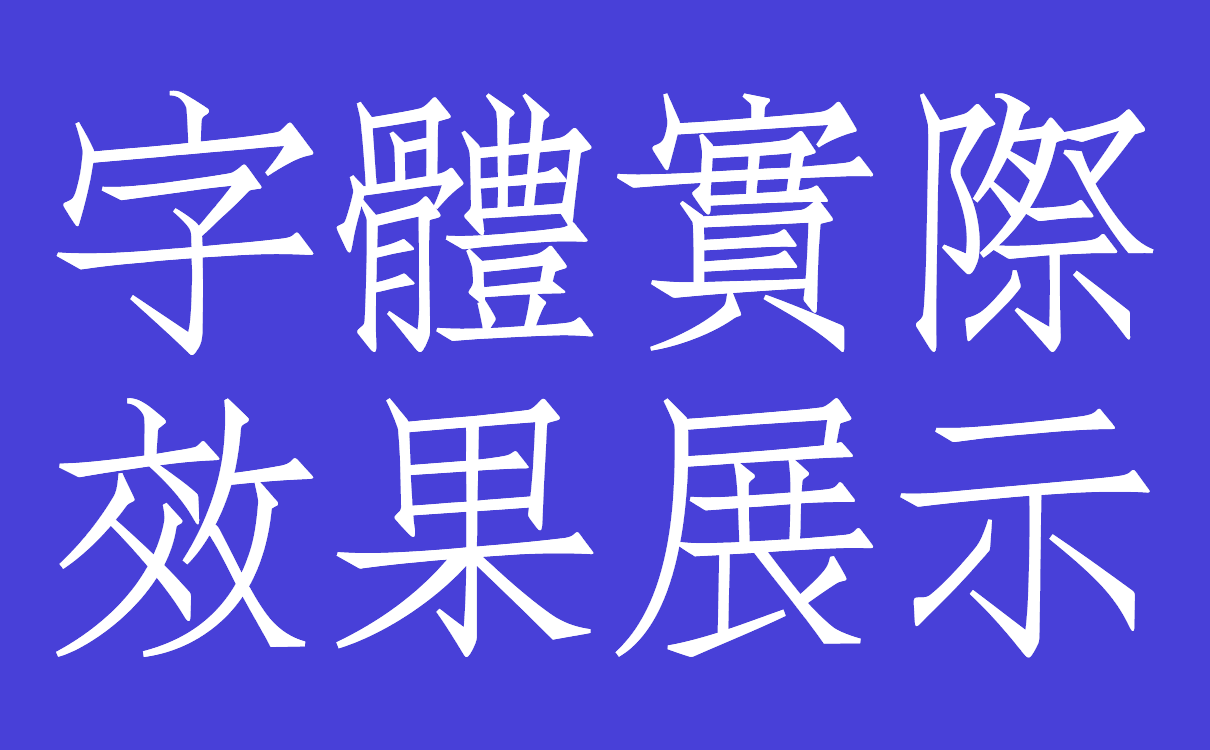
文悦民国仿宋
「文悦民国仿宋」复刻自求古斋摹宋四号方体。摹宋是民国时期除聚珍仿宋外的另一套著名仿宋铅字,它们有着不一样的个性。
本字体基本按原样进行制作,对于原字体中存在的部分文字造型不够整齐、统一的问题,我们并没有过多去纠正,而是作为一种特征,把这份不规整感继承了下来。所以,或许这并不是一款成熟、实用的字体,却是一个不那么严肃的、富有趣味的字体,适合用在一些轻松、文艺的场景里。
作为一款复古字体,本字体中特意保留了一些原字体中的手工雕刻痕迹,并采用了很多旧字形及非标准写法,同时配备了一定数量的异体字及民间俗字。